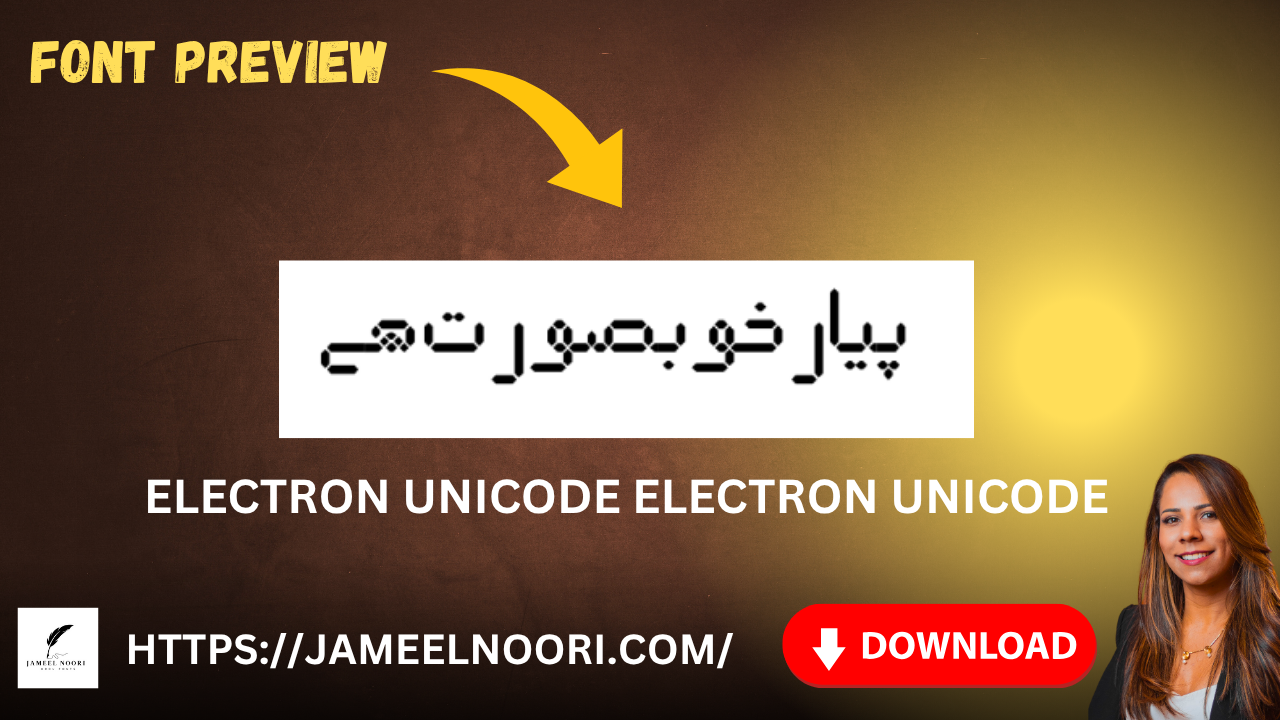
Agar aap Urdu typing ke liye ek high-quality aur stylish font dhoond rahe hain, to Download Urdu font Electron Unicode aap ke liye best choice ho sakta hai. Ye font designers, writers, aur publishers ke liye specially banaya gaya hai jo elegant aur readable Urdu presentation chahte hain.
Download Urdu font Electron Unicode ka Introduction
Key Features:
- Stylish aur Clean Unicode format
- High Compatibility with design software
- Perfect for printing aur digital content
Electron Unicode Font ka Use kahan hota hai?
Is font ka use kai jagahon par hota hai, khaaskar un logon ke liye jo Urdu me likhte ya design karte hain.
Common Usage Areas:
- Urdu blogs aur websites
- Books aur Magazine layouts
- Urdu calligraphy design
- Certificate aur invitation card designing
- Digital posters aur flyers
Best Features of Electron Unicode Font
Yeh font sirf visually appealing hi nahi balkay functionally bhi strong hai. Neeche kuch standout features diye gaye hain:
Style | Regular |
Language Support | Urdu, Arabic, Persian |
Why You Should Choose Electron Unicode Font?
Yeh font un logon ke liye perfect hai jo Professional aur Clean Urdu Typography chahte hain. Iske Unicode support ki wajah se ye font har platform aur har software me easily chal jata hai.
Conclusion – Download Urdu font Electron Unicode